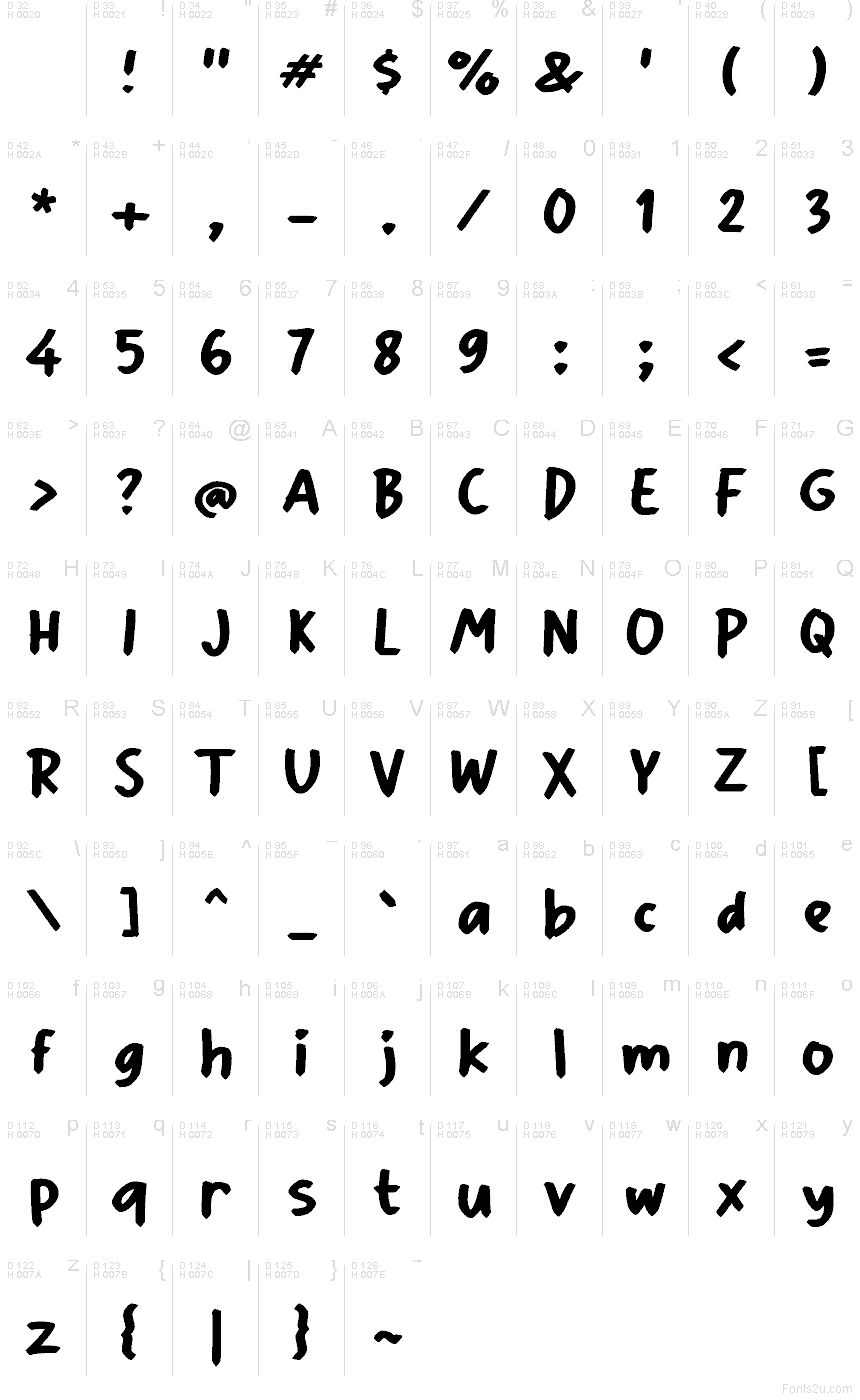
Ningur par Wep est une police brush gratuite au style brut et peint à la main, avec un grain légèrement irrégulier qui évite l'aspect trop lisse ou sage. Les lettres sont épaisses et dynamiques, avec des traits denses, des extrémités nettes et un rythme décontracté qui donne à l'ensemble une énergie très « affiche urbaine ».
Idéale pour les flyers musicaux, les graphismes streetwear, la signalétique de cafés, les étiquettes de produits ou les posts réseaux sociaux, elle apporte une touche à la fois décontractée et percutante. En tant que police gratuite, Ningur est parfaite pour les titres courts, les accroches de couverture et les cartons de titrage, car ses formes larges au pinceau rendent les mots vivants et directs, même en petit nombre.
Ningur
Présentation et spécimen de la police Ningur
Table des caractères de la police Ningur
Table des caractères de Ningur : Latin de base, page 1
Glyphes de la police Ningur — Latin de base, page 1